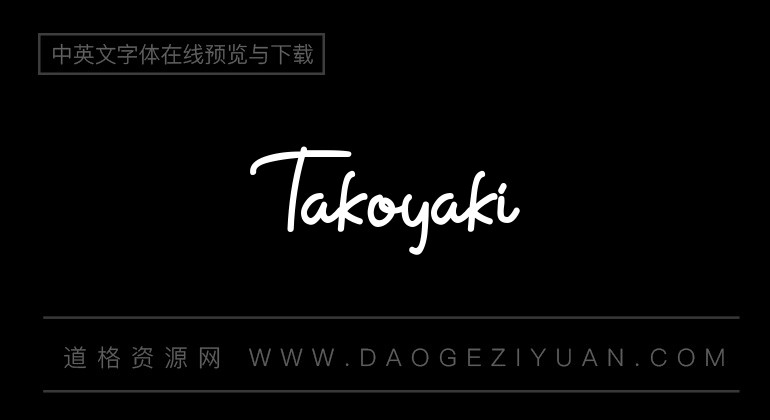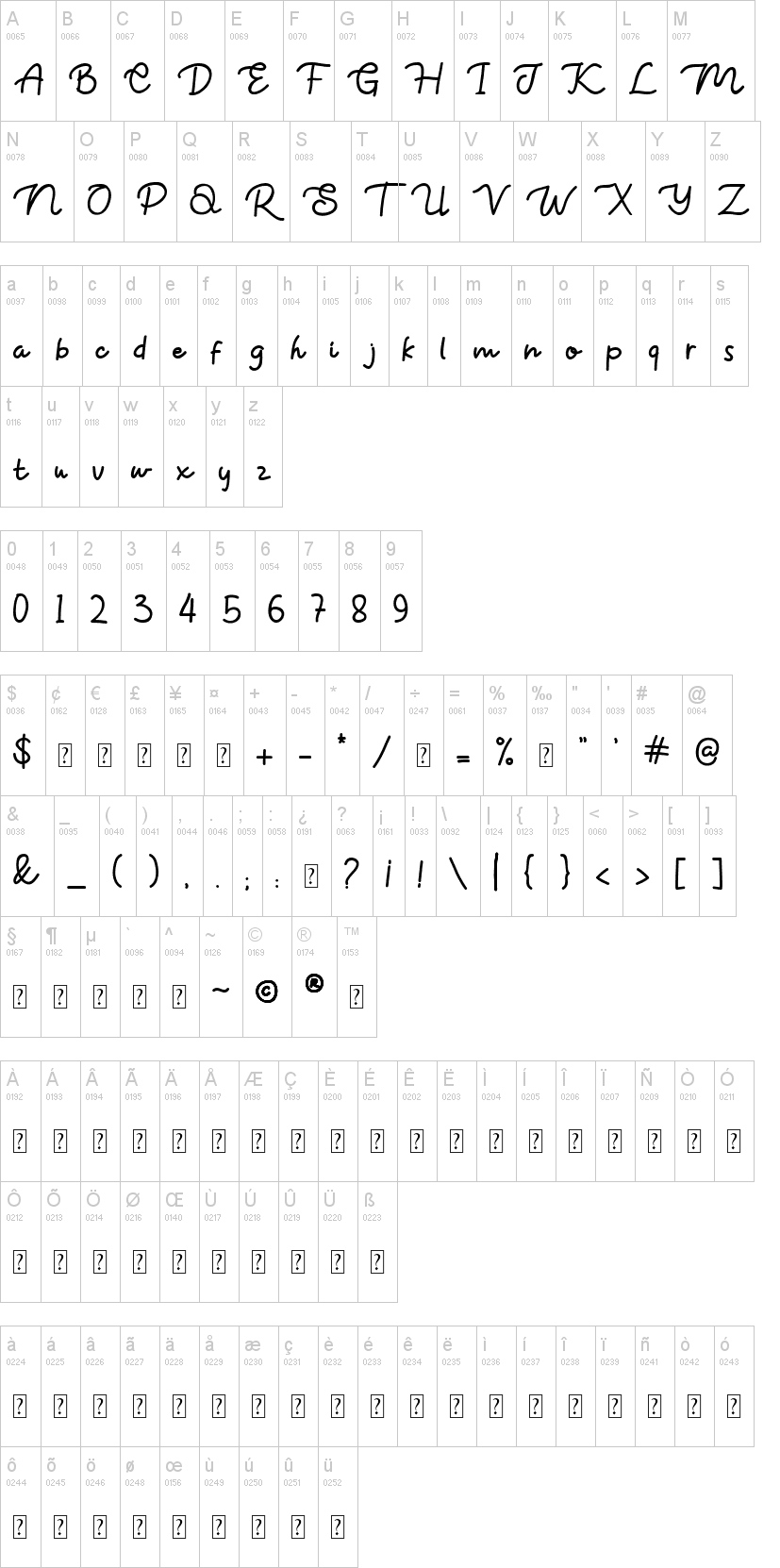
Takoyaki 是一款由日本设计师Konatsu创作的字体。这款字体以日本文化中的“章鱼烧”(Takoyaki)为设计灵感,拥有可爱的外观,细腻的线条,清晰的结构,以及浓浓的日本风格。它可以用于卡通、漫画、游戏、网站、印刷品等设计中,给您的设计带来欢乐的气氛。内容介绍
Takoyaki是一款非常不错的手写艺术字体,具有很好的视觉感,适合于文化类的宣传设计、商业类品牌的广告和产品包装设计以及个性化文字排版等较多场景。